ベビーマンスリーカード marianフォント パステルカラー
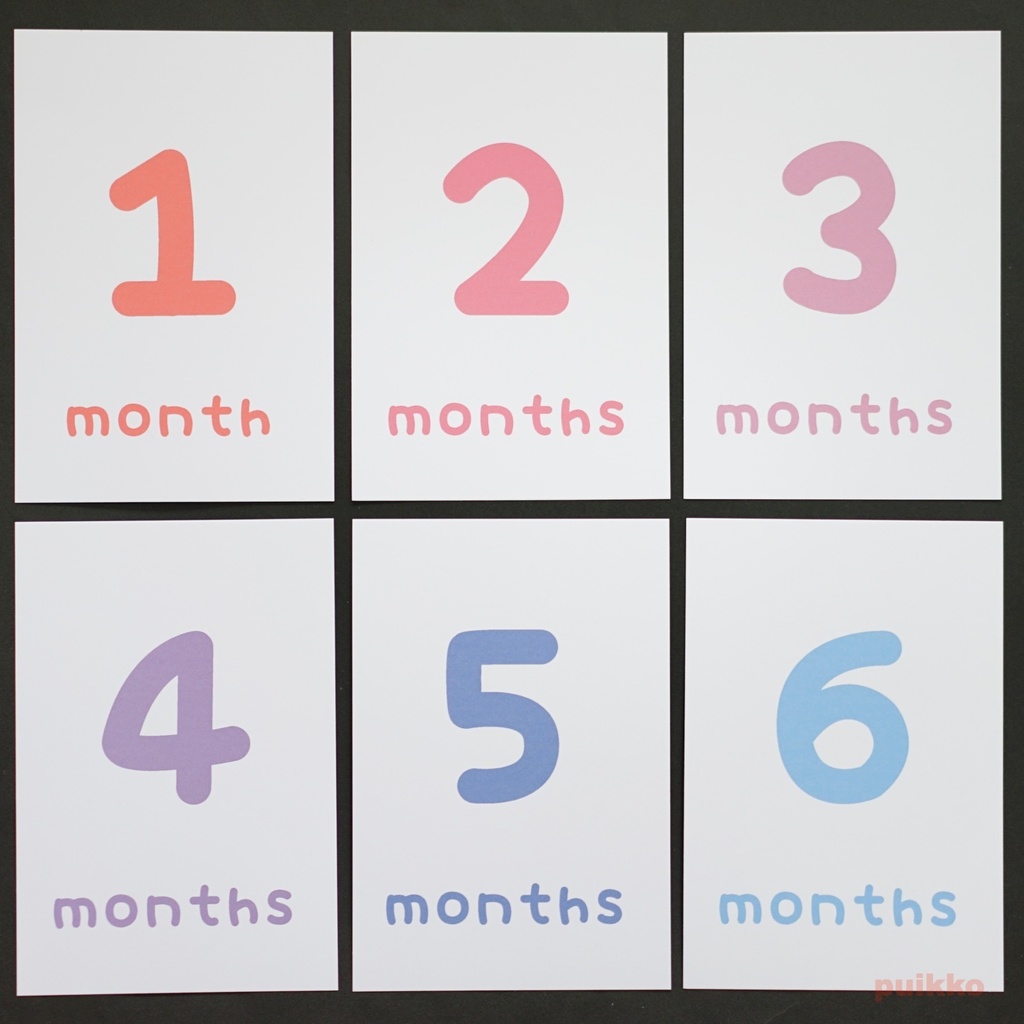
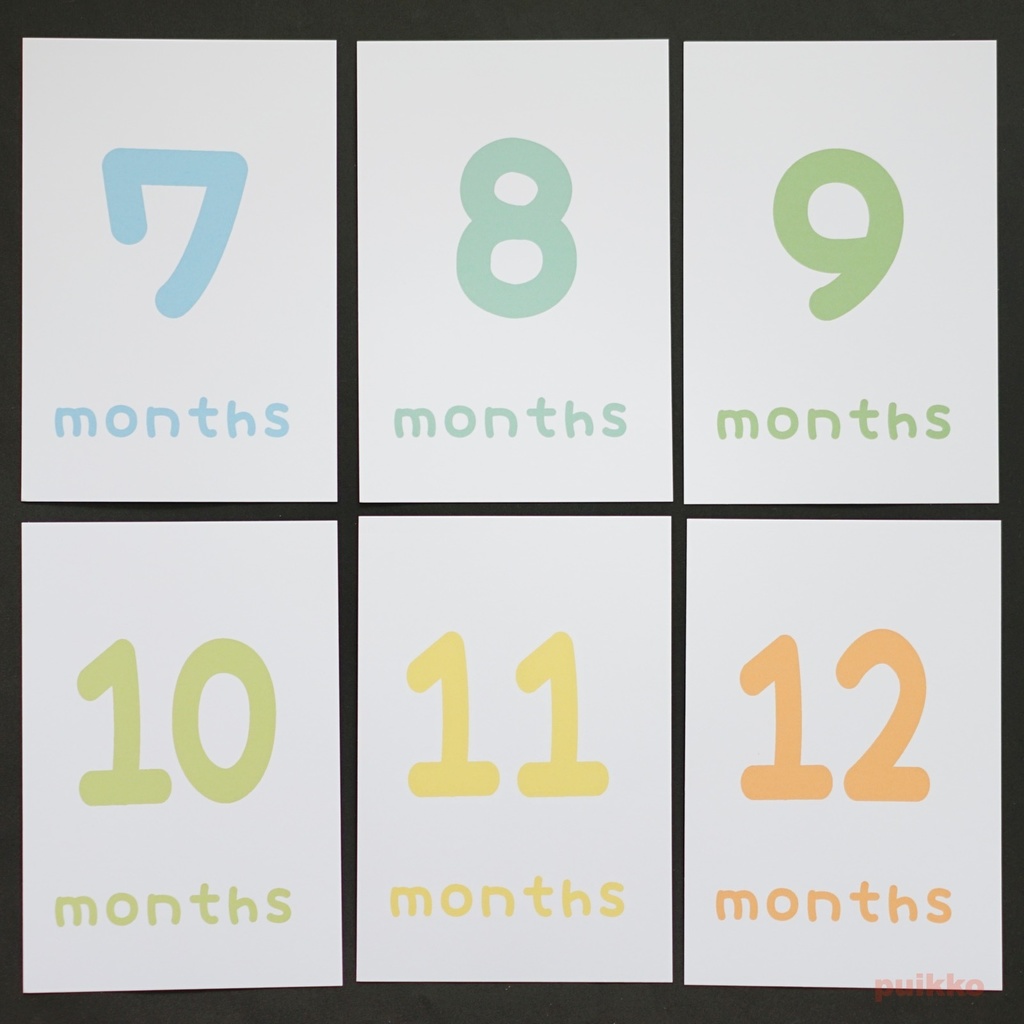
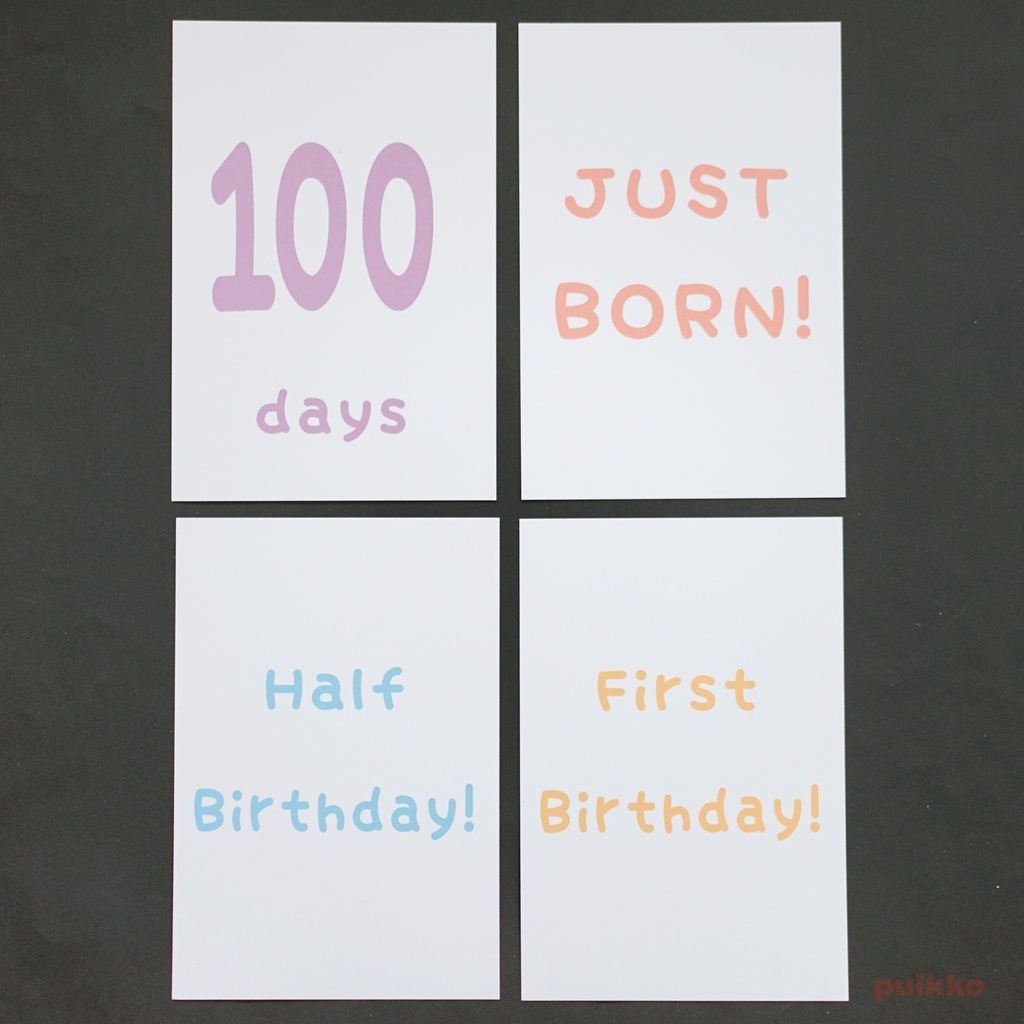
出産から1歳までの赤ちゃんの成長記録を写真に残すための月齢カード(マイルストーンフォトカード/フォトプロップス)16枚セットです。 生後1か月ごとに、赤ちゃんにこのカードを添えて撮影してください。毎月写真を撮ることによって赤ちゃんの成長がよくわかり、いい記念になります。また、裏にメモを書くなどいろいろな活用もできます。 marianフォントというpuikkoオリジナルの丸っこいフォントを使って各月ごとに色を変えて描いています。色をパステルカラーで揃えました。 JUST BORN、1~12months、100days、Half Birthday、First Birthday の16枚セット。6か月めは6monthsとHalf Birthday、12か月めは12monthsとFirst Birthdayの2パターンを用意しているのでお好みのほうをお使いください。 まとめて収納でき、撮影にも便利な卓上ケース付き。上部のフックで壁掛けにも対応。 【素材】 マット紙・厚口 厚さ0.17mm ケース PET 【サイズ】 幅100×高さ148mm(はがきサイズ)×16枚 ケース 幅103×高さ151×厚さ5mm 【購入の際の注意点】 写真と実物では多少色味が異なる場合があります。 インクジェットプリンタを使って市販の用紙に印刷し、カットしているので、精密さに欠けるところがあります。あらかじめご了承ください。 防水されていませんので紙濡れにご注意ください。 シールではありません。